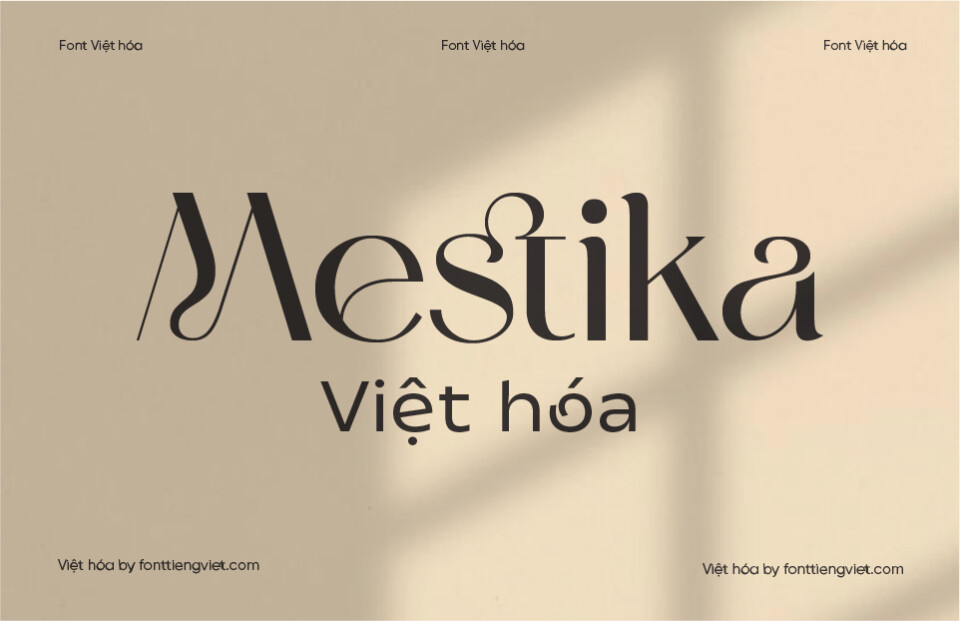
Font Việt hóa 1FTV VIP Mestika
Font Việt hóa 1FTV VIP Mestika – Bộ font chữ thiết kế sang trọng và hiện đại
Trong thế giới thiết kế đồ họa chuyên nghiệp, việc lựa chọn một bộ Font Miễn Phí chất lượng luôn là ưu tiên hàng đầu của các designer. Đặc biệt, Font Việt hóa 1FTV VIP Mestika nổi lên như một giải pháp hoàn hảo cho những ai đang tìm kiếm sự kết hợp giữa nét cổ điển và hơi thở đương đại. Đây là một bộ font Serif cao cấp, được tinh chỉnh kỹ lưỡng để phù hợp với bảng mã tiếng Việt, giúp người dùng không còn lo lắng về lỗi hiển thị dấu hay các ký tự đặc biệt khi làm việc trên phần mềm chuyên dụng.
Khám phá vẻ đẹp độc đáo của Font Việt hóa 1FTV VIP Mestika
Bộ font này gây ấn tượng mạnh mẽ nhờ cấu trúc chân chữ (Serif) thanh mảnh nhưng vô cùng chắc chắn. Sự tương phản giữa các nét thanh và nét đậm tạo nên một nhịp điệu thị giác tinh tế, mang lại cảm giác sang trọng cho mọi bản thiết kế. Font Việt hóa 1FTV VIP Mestika không chỉ đơn thuần là một công cụ truyền tải văn bản mà còn là một tác phẩm nghệ thuật, giúp nâng tầm giá trị thẩm mỹ cho các dự án sáng tạo từ bìa sách đến ấn phẩm quảng cáo.
Tính ứng dụng linh hoạt trong thiết kế thương hiệu
Với phong cách quý phái, 1FTV VIP Mestika cực kỳ phù hợp cho các dự án thiết kế bộ nhận diện thương hiệu cho các ngành hàng xa xỉ như thời trang, mỹ phẩm, hay trang sức. Các đường cong mềm mại của bộ font này giúp tạo ra những mẫu logo ấn tượng và độc bản. Ngoài ra, tính dễ đọc của font cũng cho phép nó xuất hiện trong các đoạn văn bản dài trên tạp chí hoặc website mà không gây mỏi mắt cho người xem.
Sự chỉn chu trong quá trình Việt hóa
Điểm khác biệt lớn nhất của Font Việt hóa 1FTV VIP Mestika so với các bản gốc chính là hệ thống dấu câu được thiết kế lại một cách tỉ mỉ. Các dấu thanh như dấu huyền, sắc, hỏi, ngã, nặng được đặt ở vị trí cân đối, không quá cao cũng không quá thấp, đảm bảo sự hài hòa tổng thể của con chữ. Điều này giúp các nhà thiết kế tại Việt Nam có thể sử dụng font ngay lập tức cho các tiêu đề lớn mà không cần phải chỉnh sửa thủ công bằng tay.
Cách tối ưu hóa Font Việt hóa 1FTV VIP Mestika trong công việc
Để phát huy tối đa vẻ đẹp của bộ font này, bạn nên kết hợp nó với các font không chân (Sans Serif) đơn giản để tạo ra sự tương phản. Khi sử dụng 1FTV VIP Mestika làm tiêu đề chính, hãy để khoảng cách dòng và khoảng cách chữ (kerning) thoáng đãng để bộ font “thở” và tỏa sáng. Bộ font này hoạt động tốt nhất trên các phông nền màu trung tính hoặc các tông màu trầm ấm, tạo nên sự chuyên nghiệp và uy tín cho nội dung truyền tải.
Lý do nhà thiết kế nên sở hữu bộ font này
Việc sở hữu một bộ font đã được Việt hóa hoàn thiện như 1FTV VIP Mestika giúp tiết kiệm đáng kể thời gian trong quy trình làm việc. Bạn sẽ không gặp phải tình trạng nhảy chữ hay lỗi font khi xuất file in ấn. Đây thực sự là một lựa chọn đáng giá cho thư viện tài nguyên của bất kỳ ai yêu thích sự hoàn mỹ trong từng chi tiết thiết kế đồ họa.